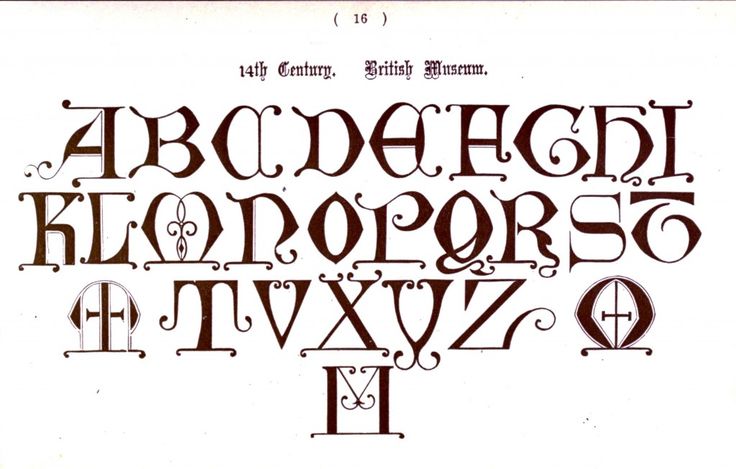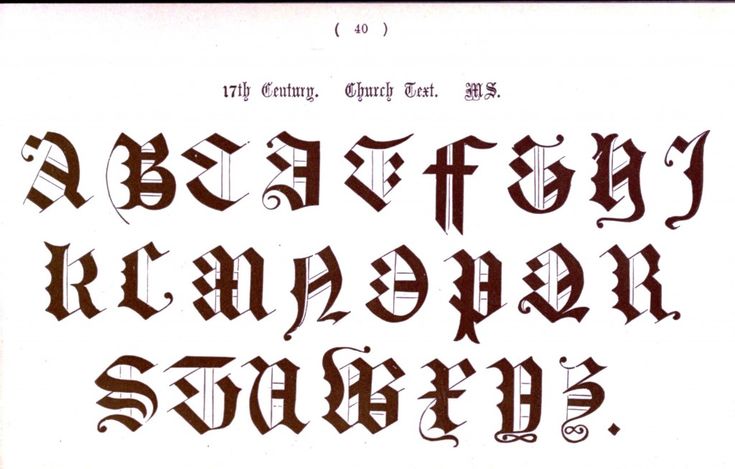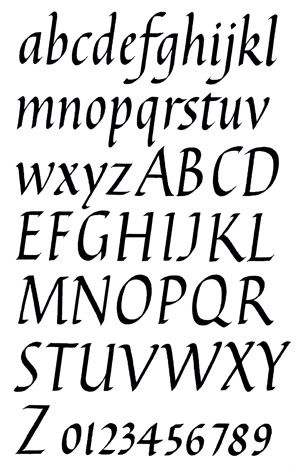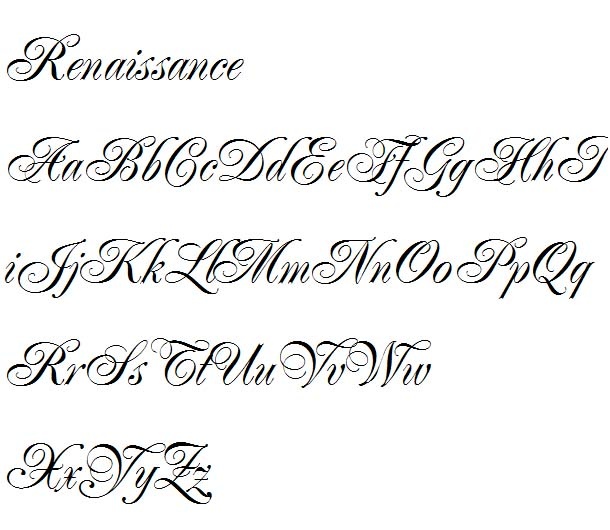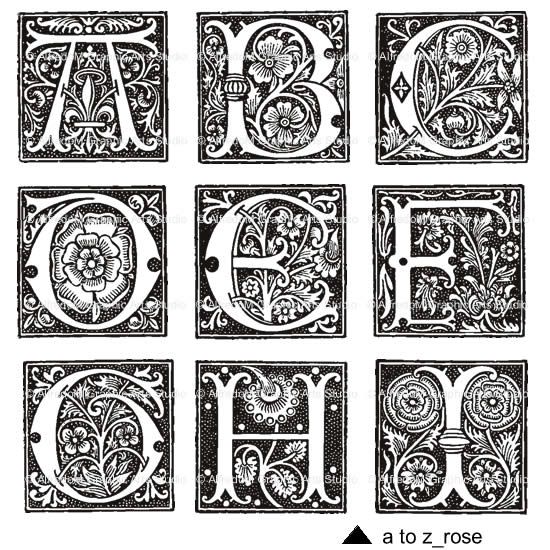
100 коллекций шрифтов из разных стилей и эпох: rentafont — LiveJournal
Это пятый из десяти постов с коллекциями шрифтов Rentafont, описанных разными способами.
Одно из главных преимуществ Rentafont – шрифтовой поиск с очень детальным описанием шрифтов из 12000 уникальных ключевых слов и опций на русском, английском и украинском языках. Таким способом описано более 3000 шрифтов с латиницей и кириллицей.
Такие данные будут полезны при обучении начинающих дизайнеров и искусственного интеллекта. Если вы генерируете дизайн с помощью алгоритмов или нейросетей, исходя из параметрического ТЗ, вам пригодятся шрифты, релевантные разным видам деятельности, техническим параметрам и особенностям аудитории.
Шрифты в разных стилях
Шрифты разных времен
Эти коллекции являются ответами на поисковые запросы из одного ключевого слова.
Уникальный поиск Rentafont состоит из 4 групп фильтров и базы словесных описаний, повторяющих и значительно дополняющих эти фильтры.
Для чего его использовать? Дизайнеры отмечают, что их последняя версия использовалась в довольно большом числе проектов по разработке фирменного стиля, от легкомысленных (крафтовое пиво) до сверхсерьезных (информационные агентства). Bookmate, популярный в России сервис подписки на электронные книги, запросил версию, которая будет работать с их приложением, что привело к разработке Kazimir Text.